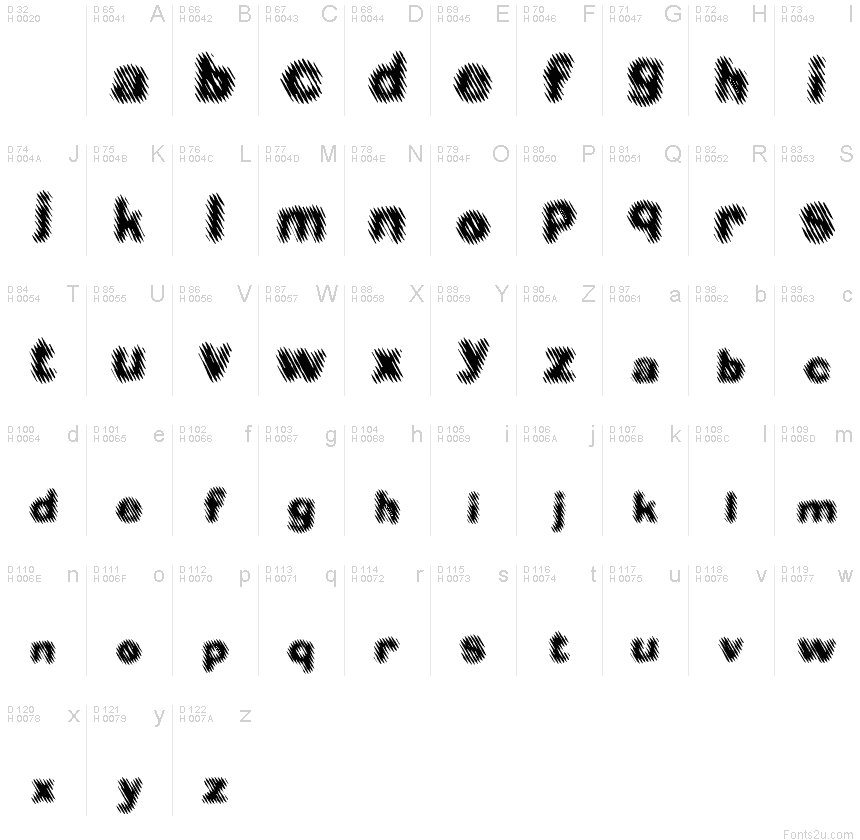
Diager to darmowy krój pisma typu display o erodowanej fakturze, z surową, poszarpaną teksturą, która wygląda raczej jak wydrapana niż narysowana. Litery zbudowane są z gęstych, ukośnych cięć, co nadaje fontowi niespokojną, wibrującą sylwetkę oraz ziarnisty, niemal zniszczony rytm w każdym słowie.
Ten dynamiczny, poszarpany styl świetnie sprawdzi się w tytułach na plakatach, ulotkach muzyki undergroundowej, okładkach horrorów, ekranach tytułowych gier czy odważnym brandingu, gdzie darmowy font musi oddać cały nastrój za pomocą zaledwie kilku znaków. Najlepiej prezentuje się w krótkich napisach, ponieważ powtarzające się ukośne blizny nadają nawet prostym słowom napiętą, surową prezencję.
Diager